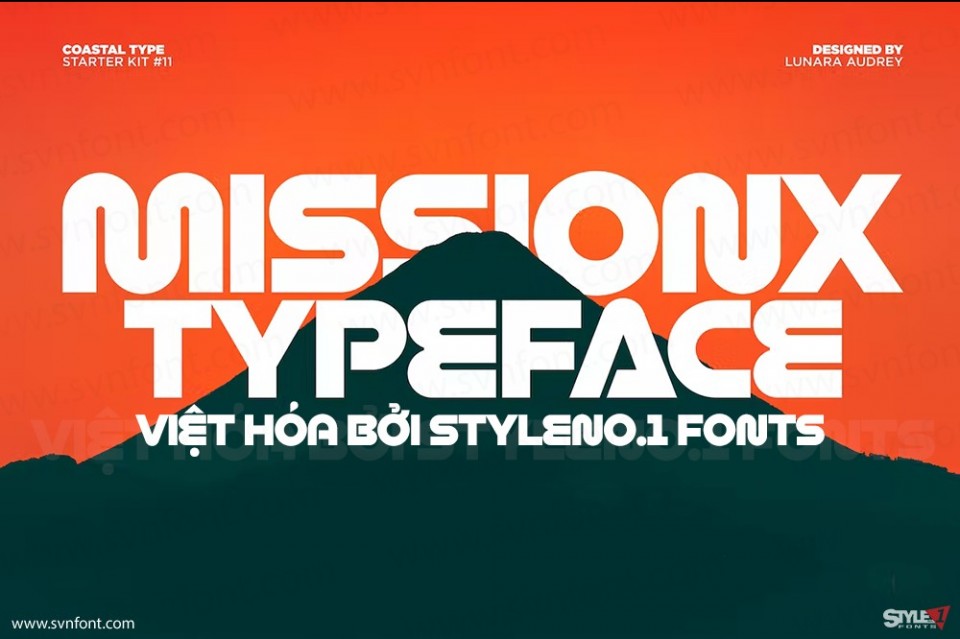
Font việt hóa SVN Mission X
Giới thiệu về Font việt hóa SVN Mission X
Trong thế giới đồ họa hiện đại, việc lựa chọn Font Miễn Phí phù hợp là yếu tố then chốt để tạo nên sự khác biệt. Font việt hóa SVN Mission X nổi lên như một giải pháp hoàn hảo cho những ai đang tìm kiếm sự mạnh mẽ và hiện đại. Đây là bộ font được thiết kế với các đường nét cứng cáp, góc cạnh, mang đậm hơi hướng tương lai và công nghệ. Việc sử dụng Font việt hóa SVN Mission X giúp các ấn phẩm truyền thông của nhà trường và học sinh trở nên sinh động, bắt mắt hơn, đồng thời đảm bảo tính thẩm mỹ cao trong từng con chữ.
Đặc điểm nổi bật của Font việt hóa SVN Mission X
Phong cách thiết kế độc đáo
Font việt hóa SVN Mission X sở hữu bộ ký tự được chăm chút tỉ mỉ, giúp hiển thị tiếng Việt một cách trọn vẹn mà không bị lỗi dấu. Với cấu trúc hình khối đặc trưng, bộ font này cực kỳ phù hợp cho các tiêu đề lớn, banner sự kiện hoặc các bài thuyết trình sáng tạo của học sinh. Sự linh hoạt trong việc kết hợp với các phong cách thiết kế khác nhau giúp Font việt hóa SVN Mission X luôn nằm trong danh sách ưu tiên của các nhà thiết kế Việt Nam.
Ứng dụng thực tiễn trong học tập
Không chỉ dừng lại ở đồ họa chuyên nghiệp, bộ font này còn hỗ trợ đắc lực cho các bạn học sinh trong việc thiết kế bìa báo tường, tập san hay các dự án học tập nhóm. Nhờ khả năng truyền tải thông điệp mạnh mẽ, sản phẩm này giúp nội dung trở nên dễ đọc và ấn tượng hơn bao giờ hết.